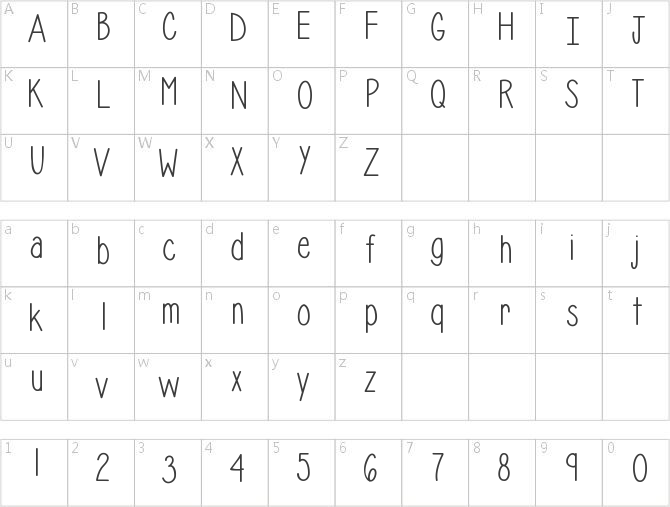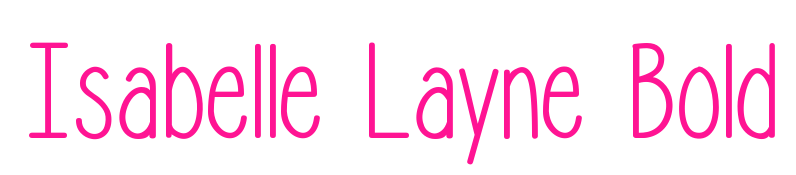
Isabelle Layne Bold 詳情頁
Isabelle Layne Bold字體字庫是一款讓人賞心悅目、百看不厭的英文字體,適合各類廣告和產(chǎn)品包裝設(shè)計應(yīng)用,字體大小0.03MB,格式為ttf字體,上傳用戶是/zyj【GF】,作者/版權(quán)方為未知